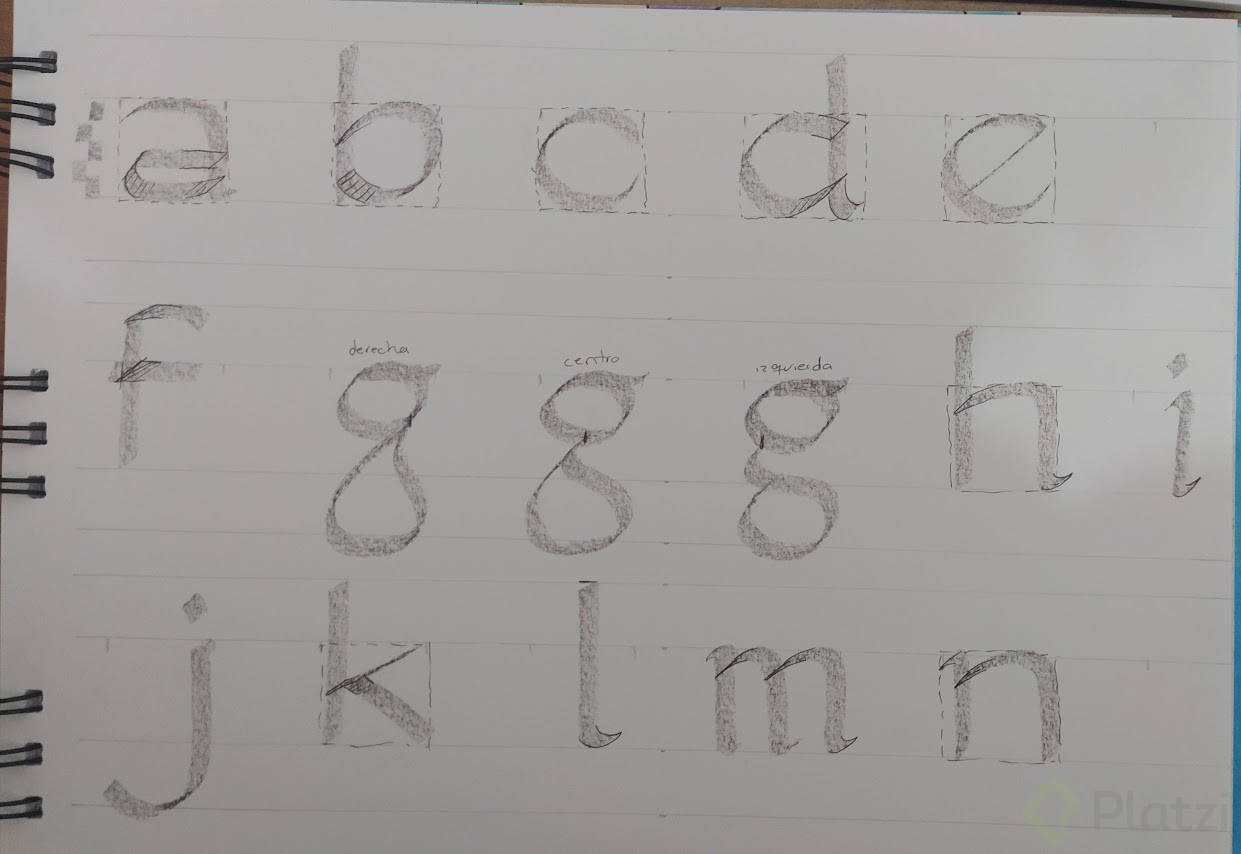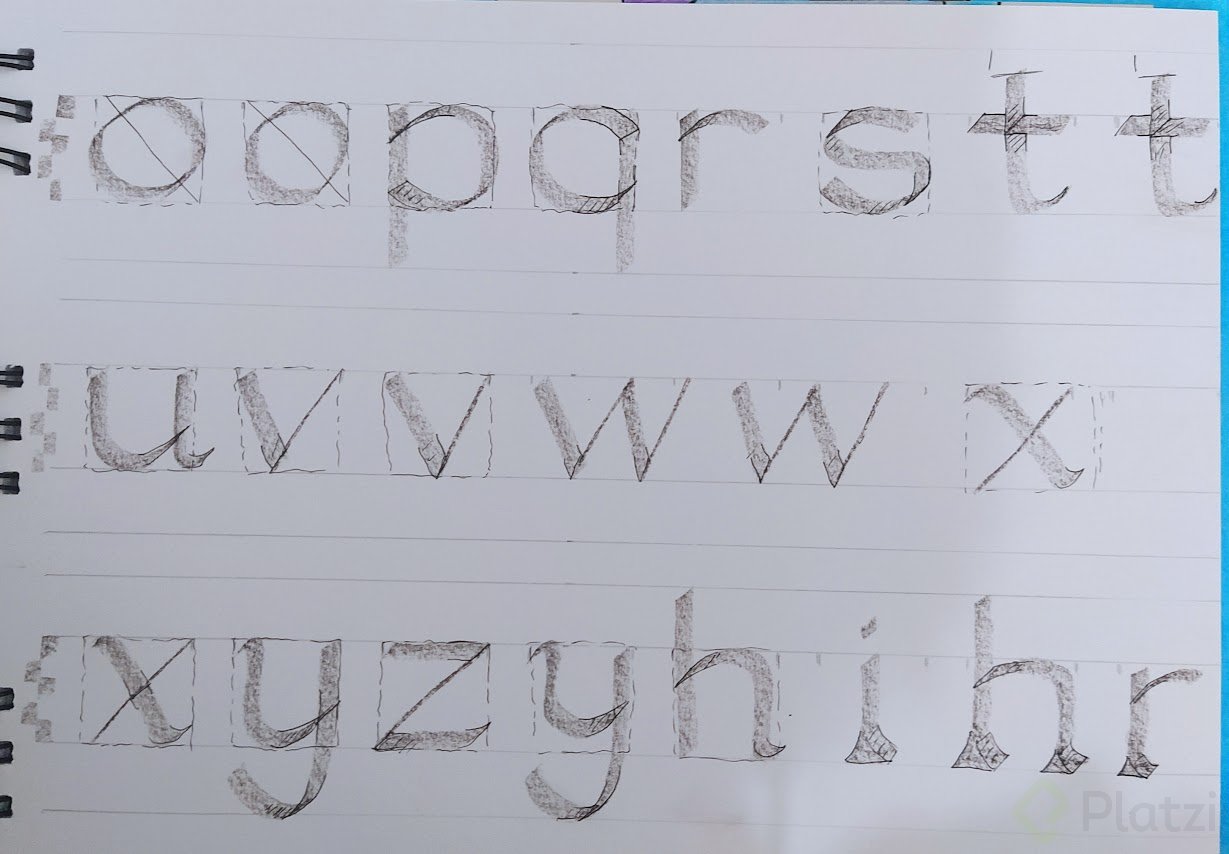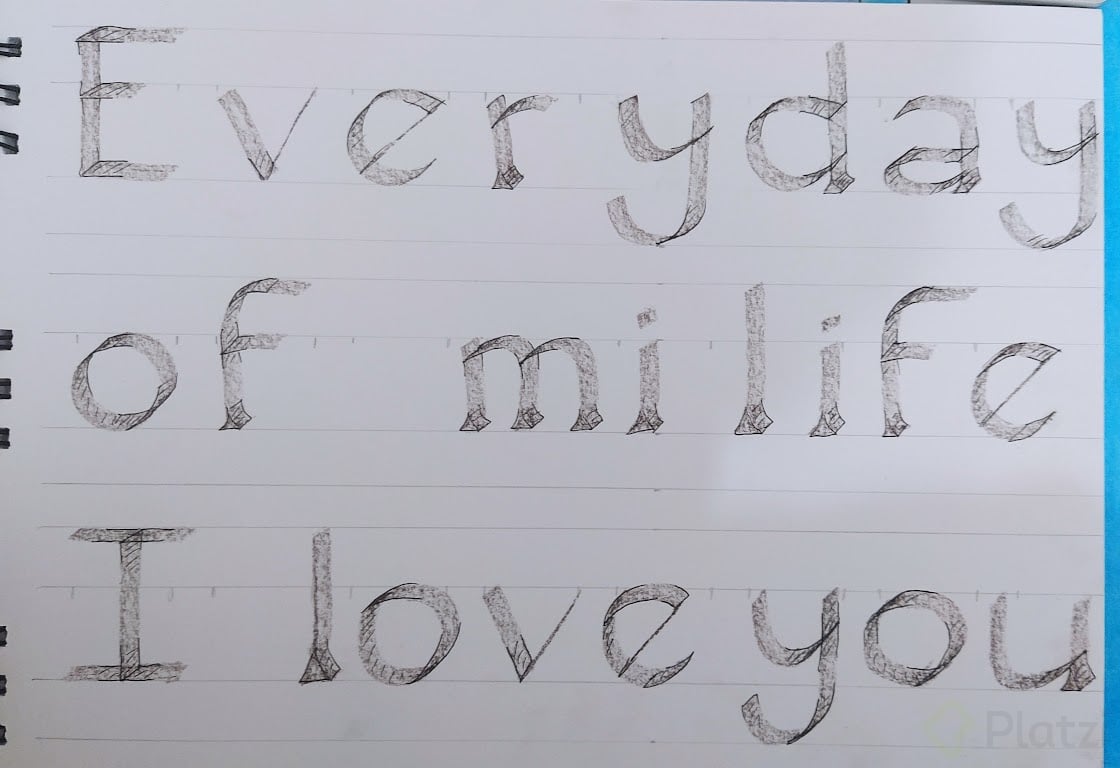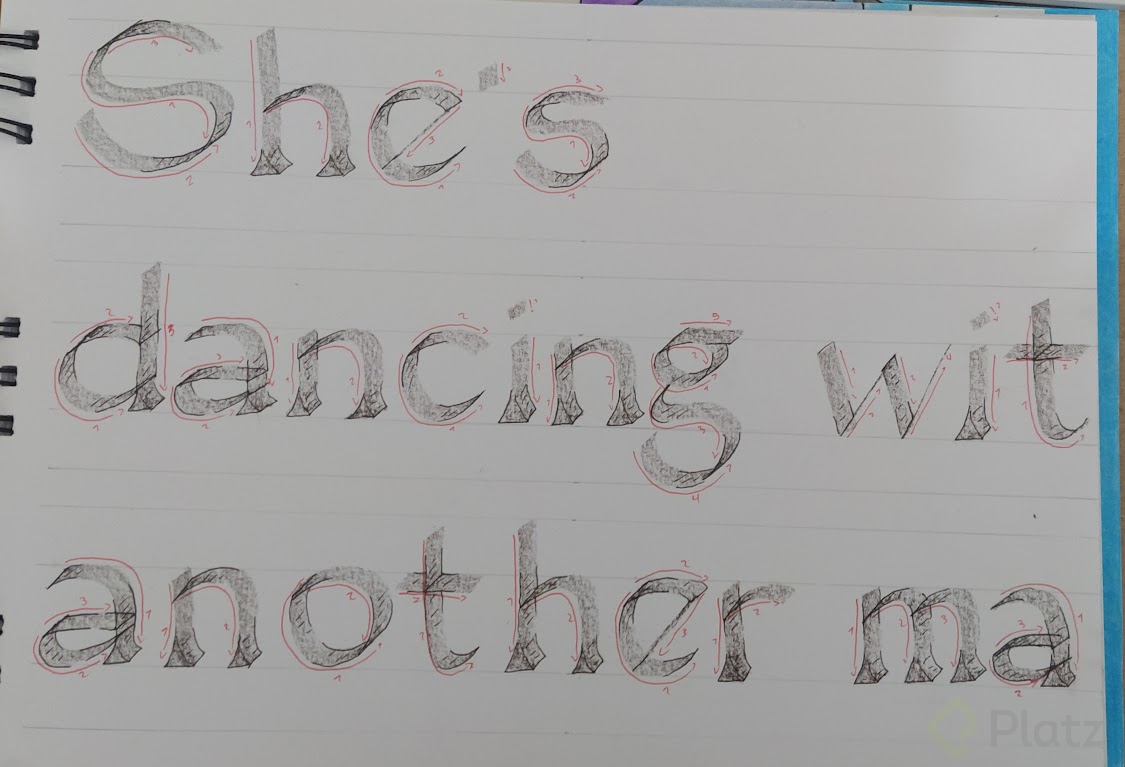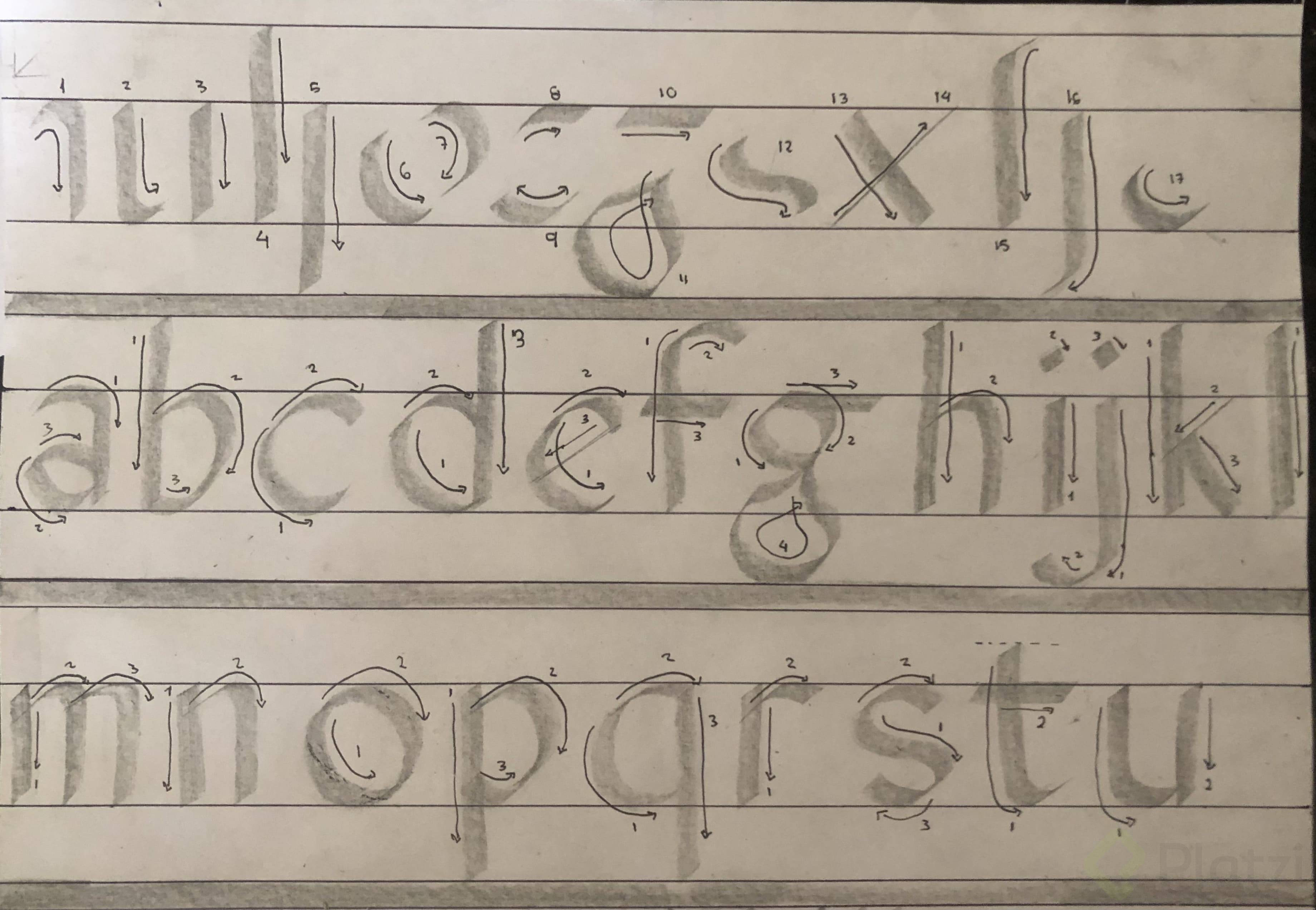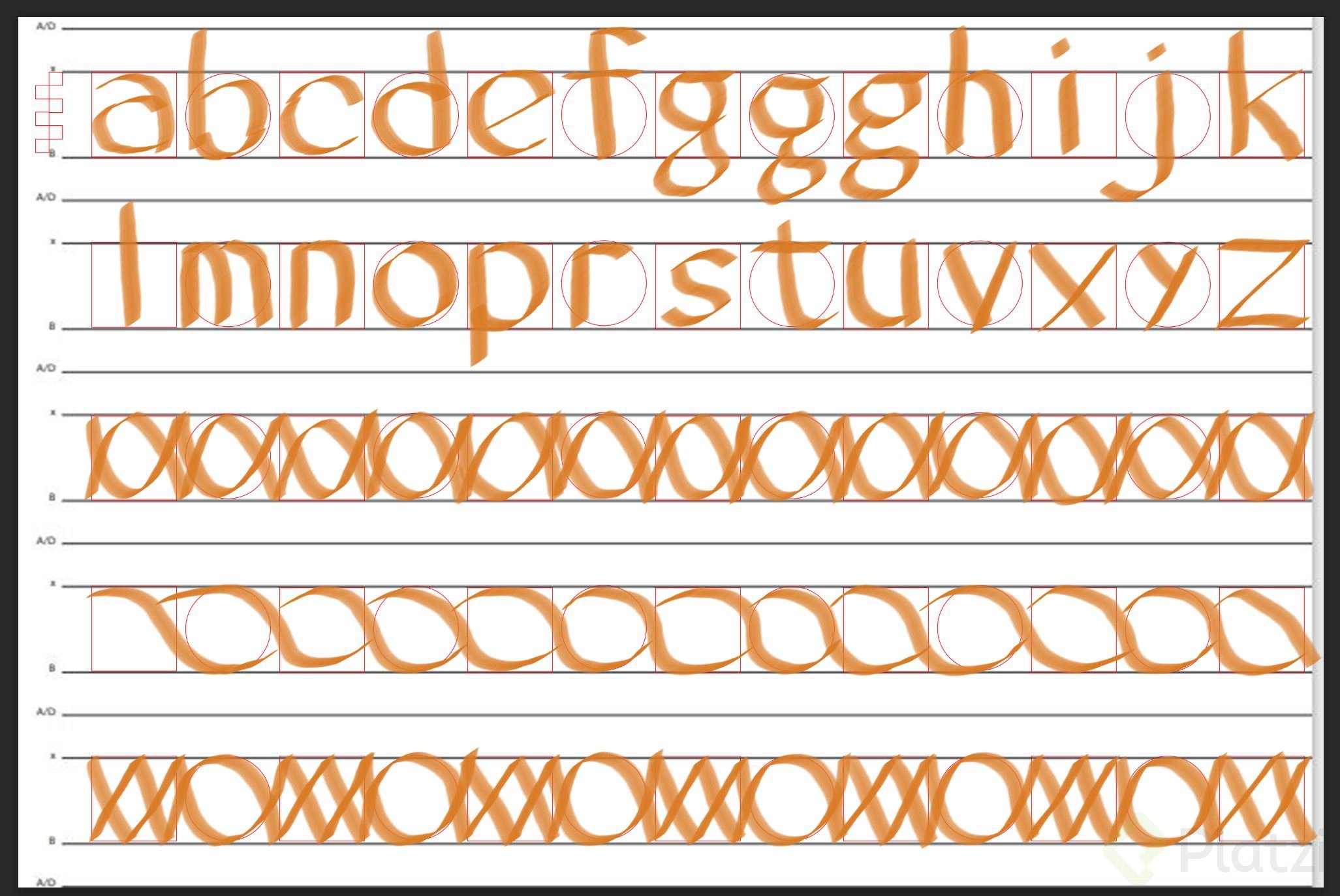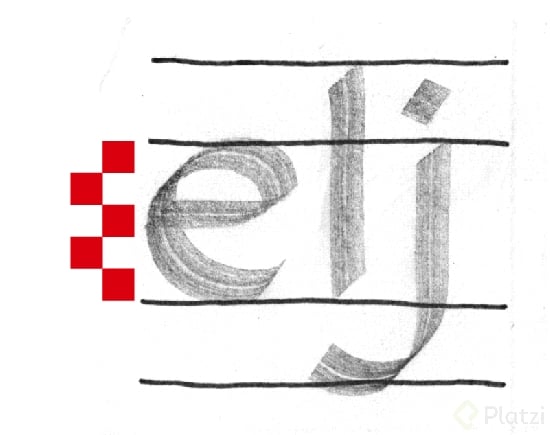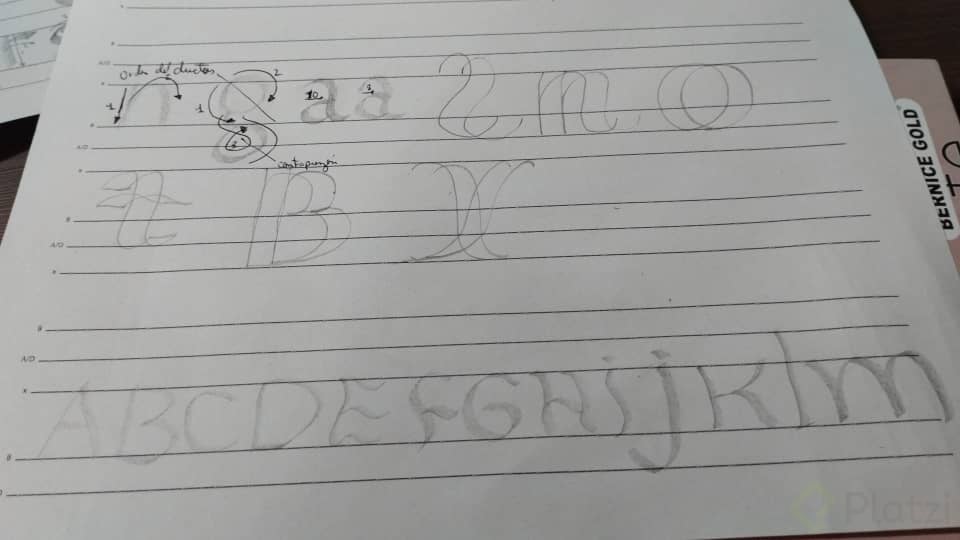
Mejoramiento de Caligrafía: Técnicas y Consejos Prácticos
En esta lectura encontrarás varios tips para mejorar tu caligrafía.
1. -Recuerda marcar el renglón caligráfico con los módulos, se recomienda poner 5 módulos para la altura de “x”.
2. Proporciona las letras para que conserven el mismo ancho, toma como referencia un cuadrado o un círculo.
3. Las letras “o” se trazan teniendo como referencia dos medias lunas que están divididas por una línea diagonal.
4. Los extremos de los trazos deben quedar empalmados así:
5. El trazo #10 que sirve para formar la “g” se puede ubicar en la parte izquierda, centro o derecha.
6. A los extremos de los trazos verticales se les puede añadir un complemento curvo o triangular.
7. El trazo ascendente de la “t” es más corto que el trazo ascendente de la “l”.